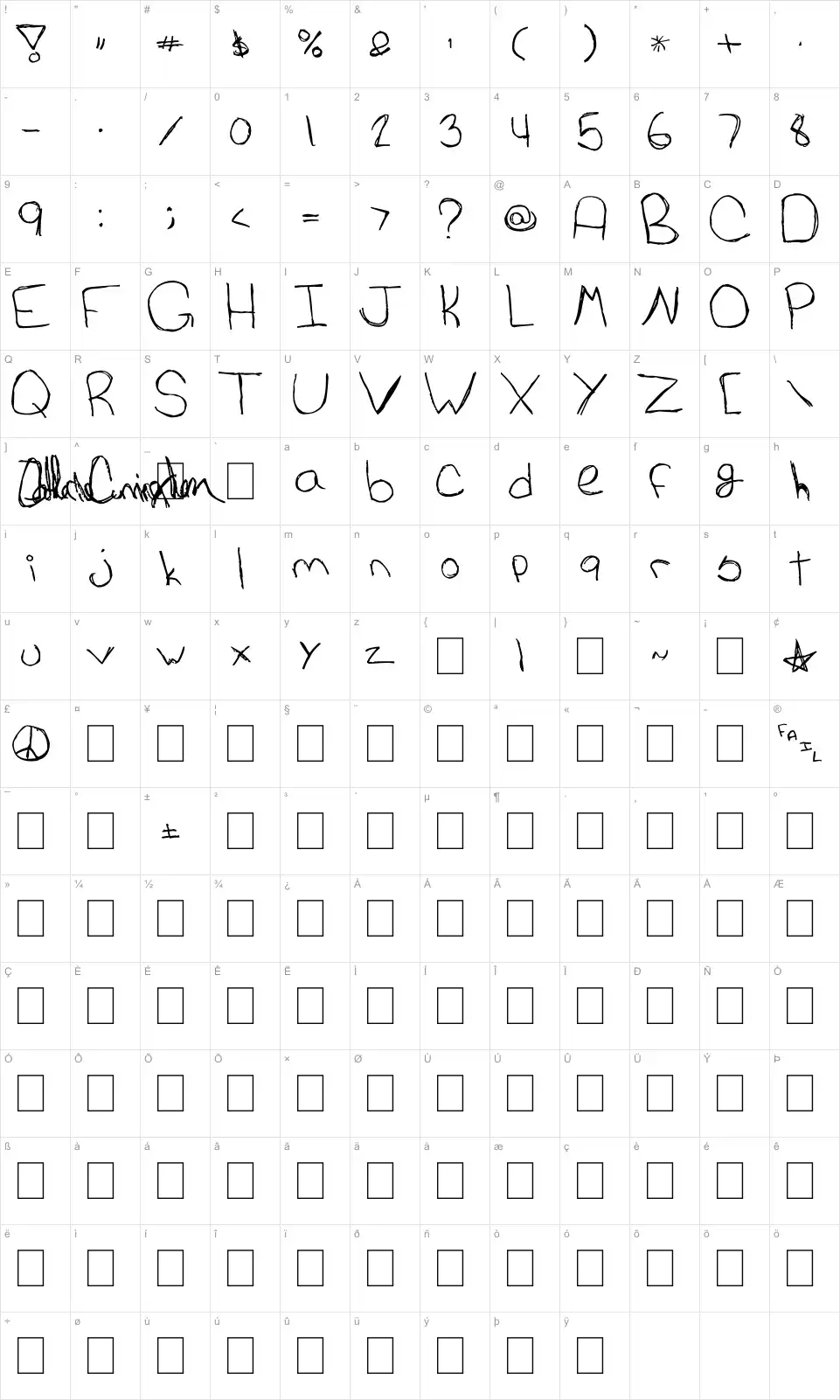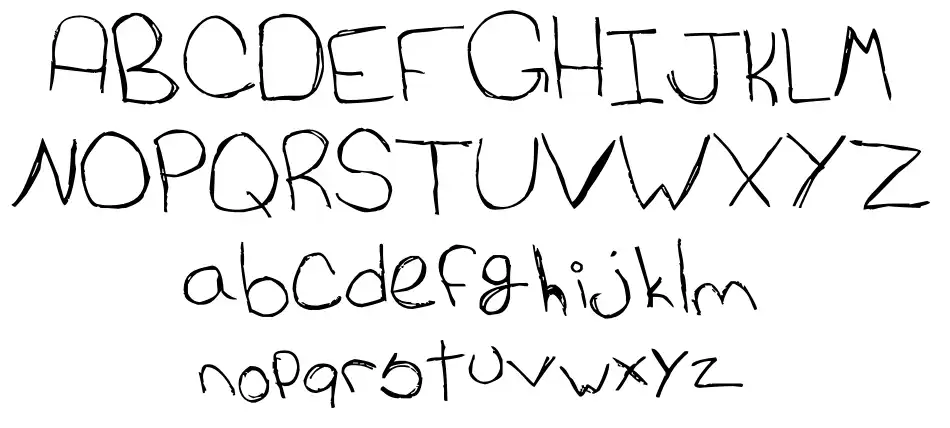
Cat’s Awesomely Awesome Font – Fonte Grátis
Cat's Awesomely Awesome Font
Descubra a Cat’s Awesomely Awesome Font, criada pela talentosa designer Catherine Cunningham. Esta fonte Script em traços manuscritos é perfeita para um toque único em seus projetos. Se você está procurando por esta fonte ou quer gerar um preview personalizado do texto, pode fazer isso online. A Fonte é gratuita para uso pessoal, disponível em formato TTF, adicionada em 12 de julho de 2022, e já foi baixada 2516 vezes. Com um tamanho de 15 KB, ela é compacta e fácil de usar em projetos digitais. Experimente agora e dê um toque especial à sua escrita.
Designer: Catherine Cunningham